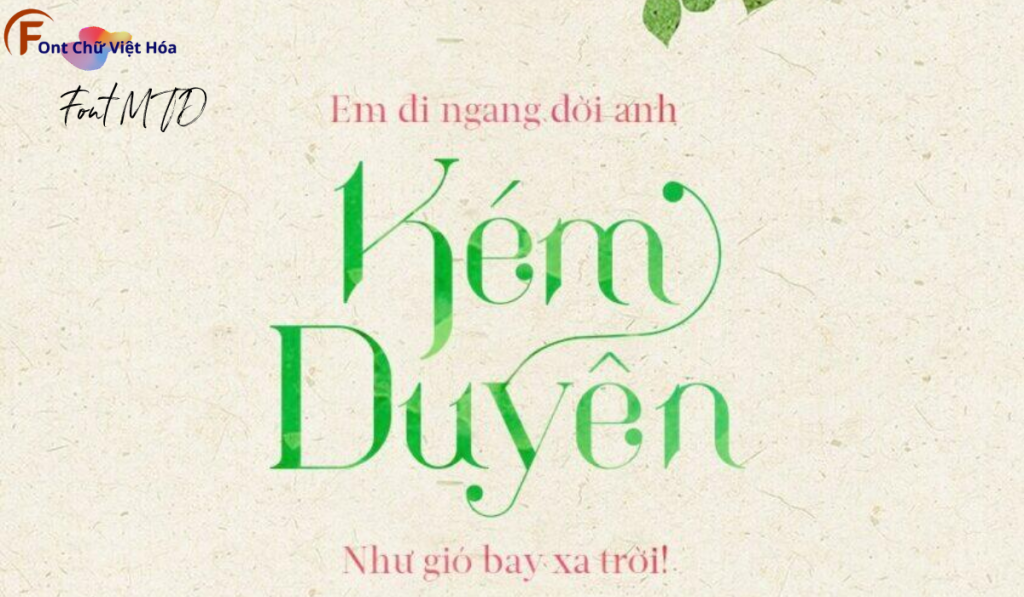
Font MTD Fashion Vogue Việt Hóa
Tác giả: Fashion Vogue Việt Hóa
Bộ Font: MTD
Phân loại: Cá tính, Độc đáo
Kiểu chữ: Có chân
Độ dày: Regular, Bold, Light
Font MTD Fashion Vogue Việt Hóa, thuộc bộ font MTD, mang phong cách thời trang và sang trọng, lý tưởng cho các dự án thiết kế như thiệp mời, bìa sách, và tài liệu văn phòng. Với các nét chữ có chân và độ dày đa dạng, Font MTD Fashion Vogue Việt Hóa không chỉ dễ đọc mà còn tạo cảm giác lịch lãm và chuyên nghiệp. Việc Việt hóa font giúp người dùng dễ dàng tích hợp vào các thiết kế tiếng Việt, mang lại sự tiện lợi và nâng cao tính thẩm mỹ.